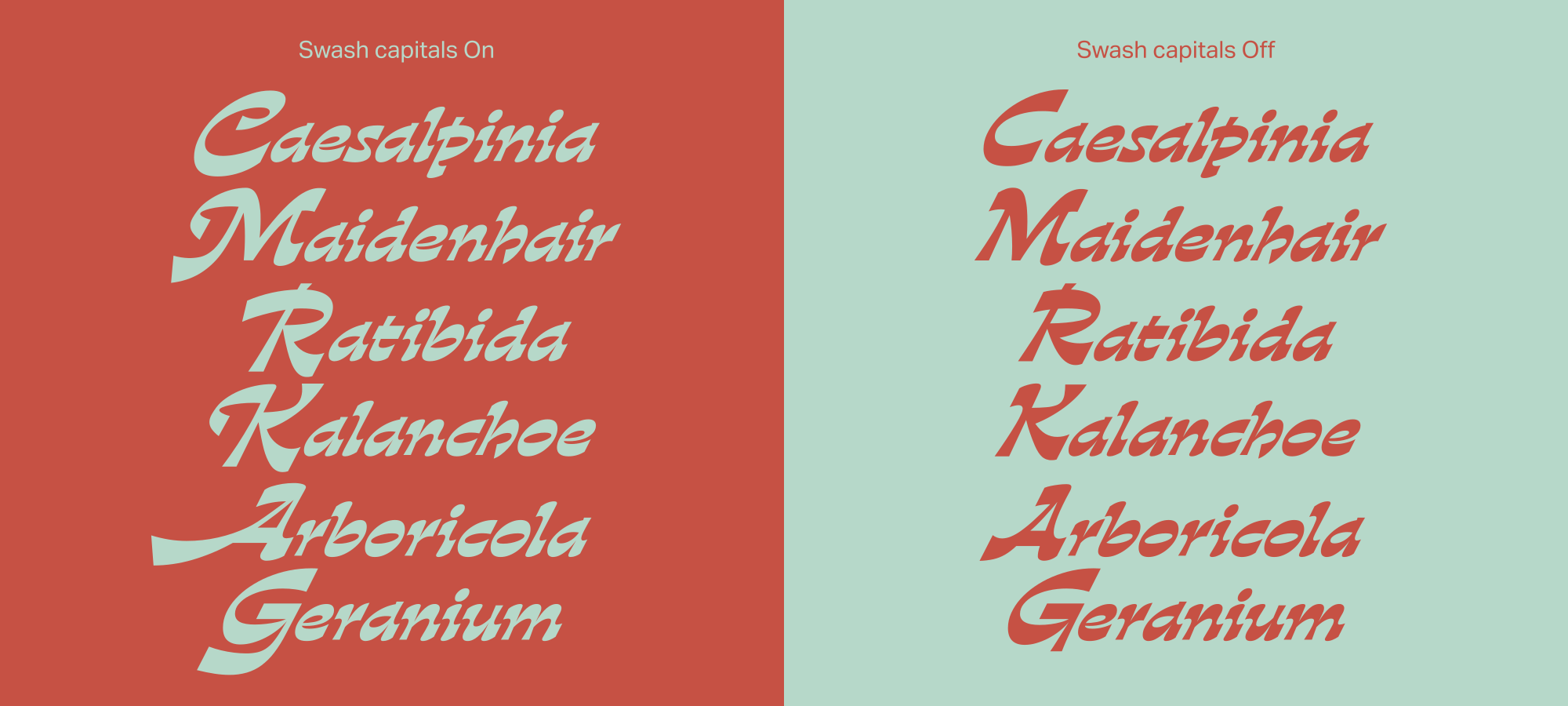
Gardez Font
Description de Gardez Font
Gardez est une police d’affichage accrocheuse, conçue pour être utilisée dans de grandes tailles et dans de courts passages de texte. Ses caractéristiques très expressives en font un choix idéal pour les emballages, les logotypes, les affiches, les titres de magazines et les couvertures de livres.
Gardez est né de la fusion des formes et des caractéristiques typiques de l’italique garalde traditionnel avec celles d’un motif contrasté inversé – deux styles traditionnellement très éloignés. Dans le design contemporain, les tabous visuels tombent et il existe un appétit insatiable pour les designs peu orthodoxes et stimulants ; nous avons vu une opportunité d’être courageux et irrévérencieux en combinant deux extrêmes en quelque chose de très nouveau et de très différent.
Le concepteur de Dalton Maag, Rafael Saraiva, a développé une police d’affichage unique et parfaitement exécutée qui capte l’attention du lecteur et reste avec lui. Gardez prend des libertés que seules les polices d’affichage numérique peuvent offrir : des majuscules extrêmement grandes, des ornements sans vergogne et des traits fluides et expressifs qui défient délibérément les lois de la lisibilité.